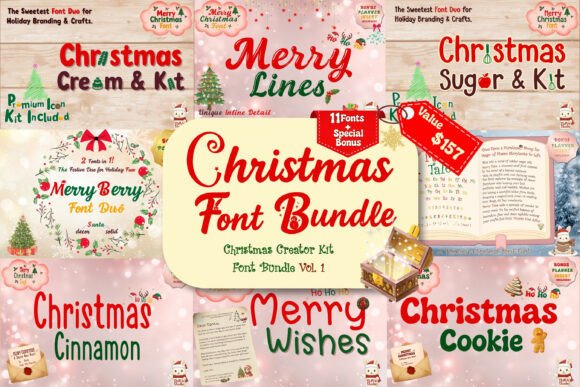
Christmas Font Bundle
Het vinden van de juiste ontwerpelementen kan lastig zijn, maar Christmas Font Bundle biedt een uitzonderlijke collectie die uw werk direct naar een hoger niveau tilt.
Of u nu POD-producten (Print on Demand), huwelijksuitnodigingen of afbeeldingen voor sociale media maakt, Christmas Font Bundle is een ideale keuze.